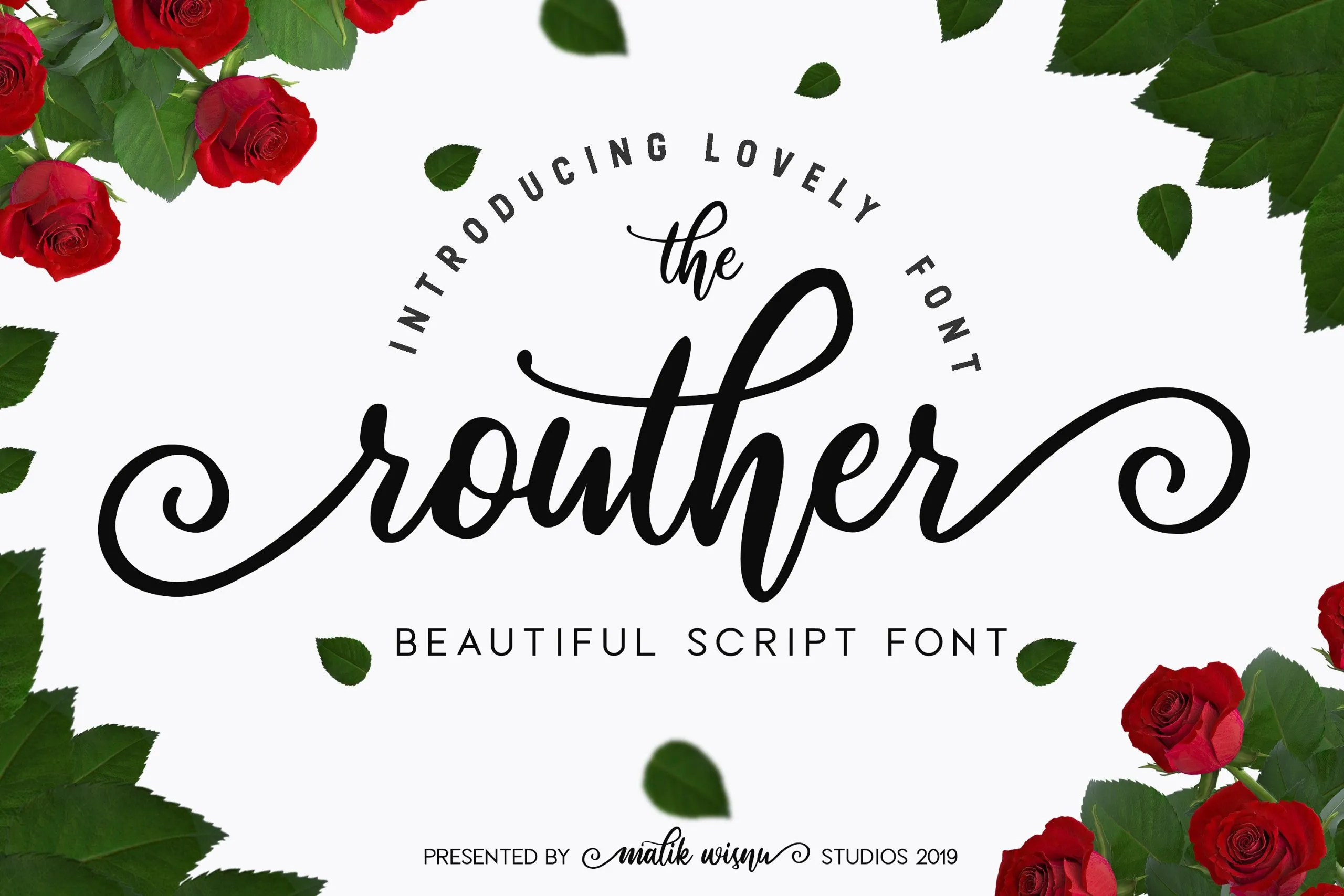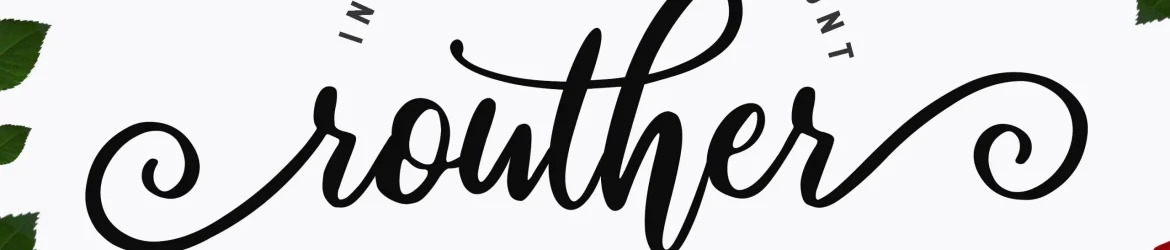
Esta é uma fonte de escrita a mão original perfeita para dar um toque autêntico aos seus projetos. Routher Script Font foi criado para inspirar com objetos bem-feitos e lindamente desenhados, tornando-o moderno e imponente em inúmeras maneiras para seu próximo projeto. Este script é ideal tanto para logos e marcações quanto para fotos, convites, marcas de água, anúncios, design de produtos, estaçãoaria, designs de casamento, etiquetas ou embalagens, eventos especiais ou qualquer coisa que precise de um toque único. Routher Script é uma fonte que traz originalidade e estilo a qualquer projeto, tornando-a perfeita para quem busca uma sensação única em suas criações gráficas.